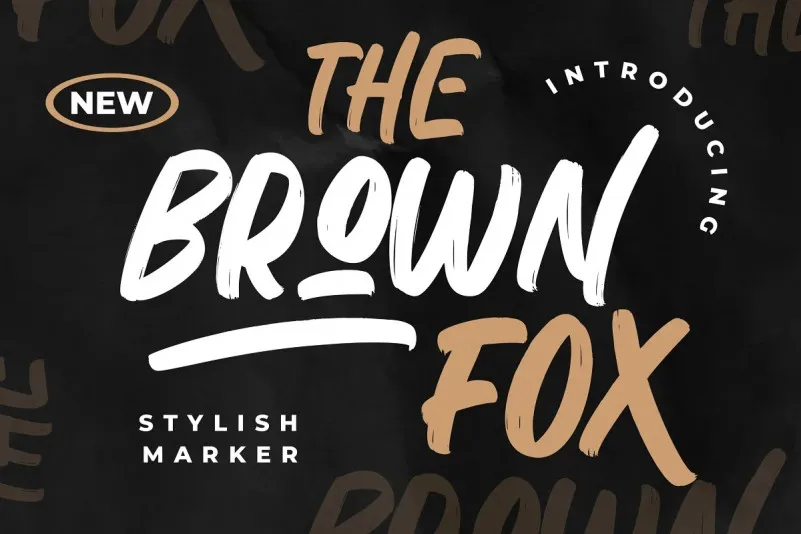
The Brown Fox Font – Fonte Grátis
The Brown Fox Font
A “Brown Fox” é uma elegante fonte brush que oferece um toque moderno e sofisticado a qualquer projeto design. Ela foi criada para transformar seu trabalho nas seções de destaque ou logomarcas, desde projetos de wedding até banners de mídia social. A Fonte Brown Fox é perfeita para os desafios do branding. Sua facilidade em adaptar-se às necessidades específicas de projeto torna-a uma opção ideal para a criação de logotipos, design de embalagens e até mesmo etiquetas. Com seu toque único e vibrante, a “Brown Fox” se destaca em qualquer formato ou estilo de design. Ideal tanto para publicações online como para designs impressos, esta fonte captura a essência da escrita manual, adicionando um toque autêntico às suas criações digitais. Seja para anúncios, papelaria, convites de casamento, ou qualquer outro projeto que busque incorporar o brilho e a personalidade do estilo de escrever por conta própria. A “Brown Fox” é sua fonte perfeita para trazer vida às suas criações, proporcionando um toque delicado e moderno.